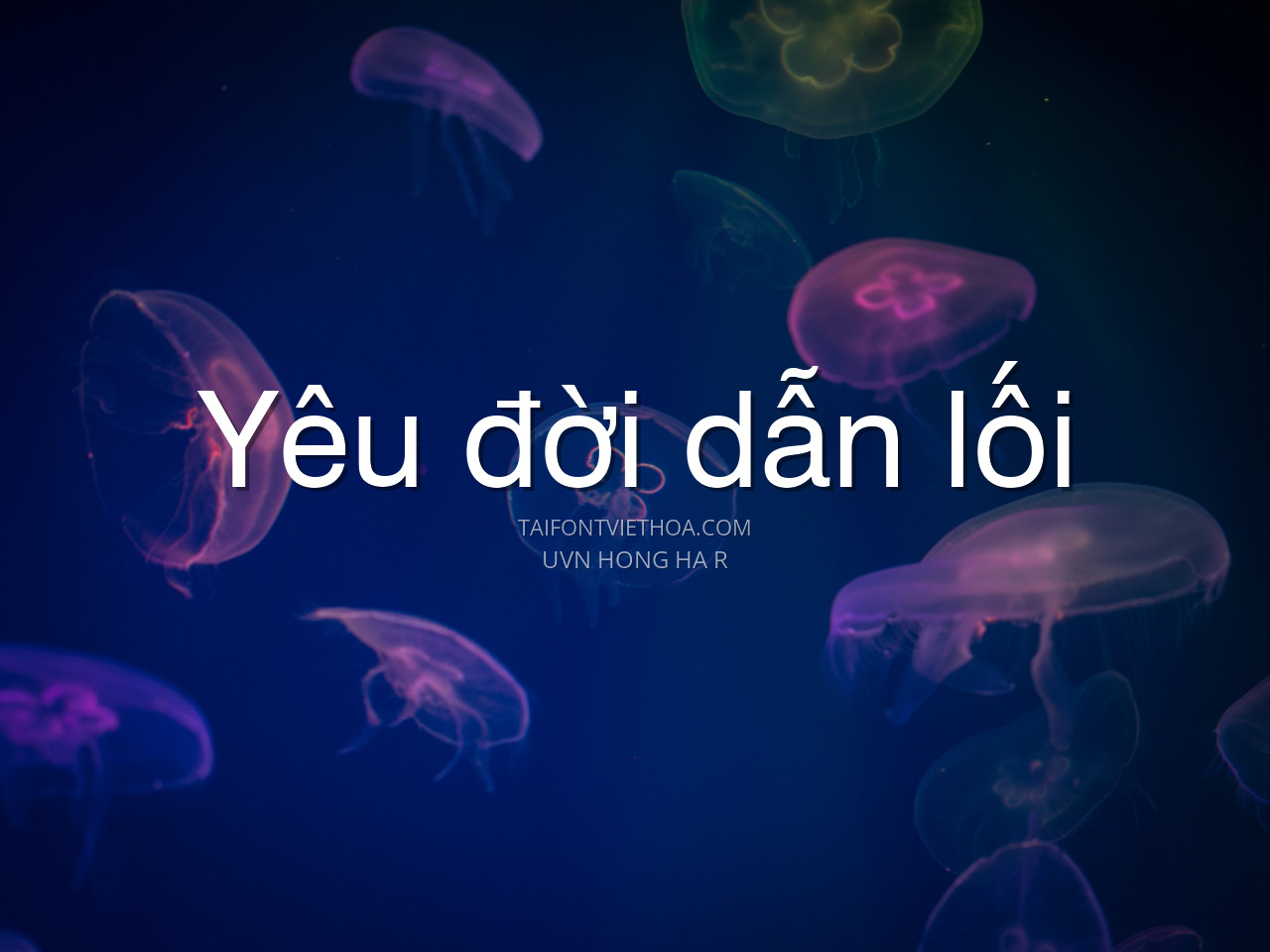
Giới thiệu về font UVN Hong Ha
UVN Hong Ha là một font chữ mang tính truyền thống, gợi nhớ đến hình ảnh dòng sông Hồng lịch sử – biểu tượng của văn hóa, thơ ca và sự trù phú của đất Bắc Việt Nam. Với thiết kế đơn giản, dễ đọc và hơi hướng retro, font này thường xuất hiện trong các ấn phẩm mang tính giáo dục, truyền thống hoặc tài liệu văn hóa. UVN Hong Ha được sưu tầm và chia sẻ bởi thành viên Font Chuẩn, đồng thời được taifontviethoa.com lựa chọn để phục vụ cho các dự án thiết kế liên quan đến giáo dục, văn hóa và in ấn tài liệu chính thống.
Đặc điểm thiết kế và ứng dụng của UVN Hong Ha
Font UVN Hong Ha thuộc nhóm sans-serif với các nét chữ dứt khoát, độ dày đồng đều và tỷ lệ ký tự cân đối. Phong cách trình bày nghiêm túc, rõ ràng giúp người dùng dễ dàng sử dụng trong các văn bản hành chính, bài giảng hoặc thiết kế sách giáo khoa. Font hỗ trợ đầy đủ tiếng Việt và có độ tương thích cao với các phần mềm văn phòng cũng như trình bày đồ họa hiện đại.
Ứng dụng phù hợp: giáo trình, sách học sinh, tiêu đề báo tường, slide giảng dạy, tài liệu văn hóa. Ngành nghề phù hợp: giáo dục, xuất bản, truyền thông xã hội, thiết kế tài liệu hành chính, dự án cộng đồng và các nội dung truyền thống.